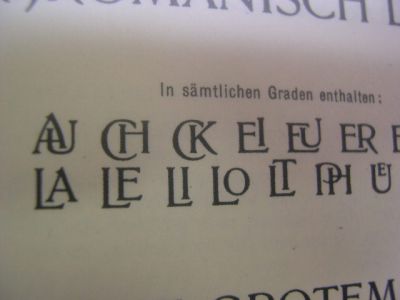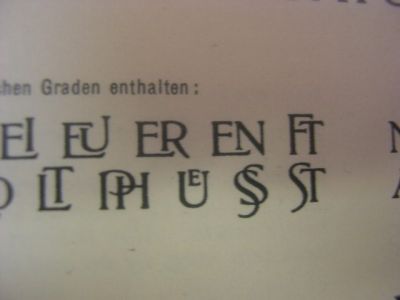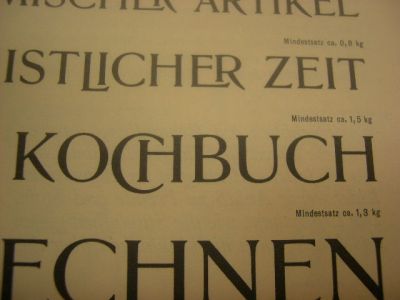
Schrift gesucht
Vorweg Entschuldigung für die miserable Qualität … Kennt jemand die (oder eine ähnliche) Schrift auf diesem Titelblatt mit den merkwürdigen Überlappungen?
Diese Schrift war im Programm von Schelter & Giesecke aus Leipzig.
In einem Schriftmusterbuch (in französicher Sprache), das um die vorletzte
Jahrhundertwende erschienen ist, fand ich die
"Roman No 20" zu der es ebenfalls ein Schnitt mit Ligaturen gab.
"Ligatures (entrelaçées) pour Roman No 20" (siehe Bild).
Eine "Roman Demi-Gras", halbfette Roman, gab es auch.
Dazu der Schnitt "Ligatures pour Roman Demi-Gras".
Ich wußte, ich finde diese Schelter & Giesecke-Schrift..
Das sind Ligaturen zur Anker-Romanisch. Erstguß um 1908.